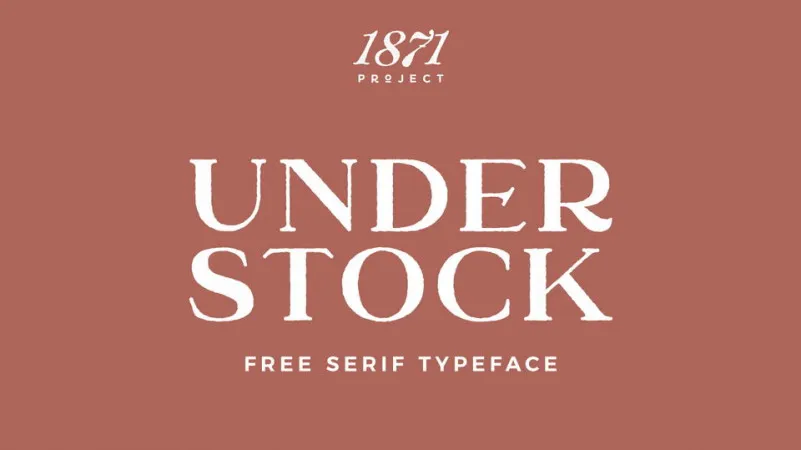
Understock Serif Font – Download Grátis
Esta é uma família de fontes serif vintage inspirada nos antigos posters gráficos. Ela foi projetada para dar um toque nostálgico a qualquer projeto visual, com suas formas de letra que apresentam pequenas curiosidades, criando um equilíbrio perfeito entre seriedade e imperfeição bruta. Hamilton é o designer responsável por esta fonte elegante e versátil, ideal para aplicar em diversas criações vintage. Com traços suaves e recursos opentype, a Understock Serif Font se destaca como uma ferramenta indispensável para aqueles que desejam incorporar um estilo retro em seus trabalhos. Suas características criadas à mão garantem uma personalidade única, tornando-a perfeitamente adaptável a criações vintage, desde design de marca e identidades pessoais até logotipos, embalagens de produtos, cartões de convite, citações e até mesmo rótulos de panflet.